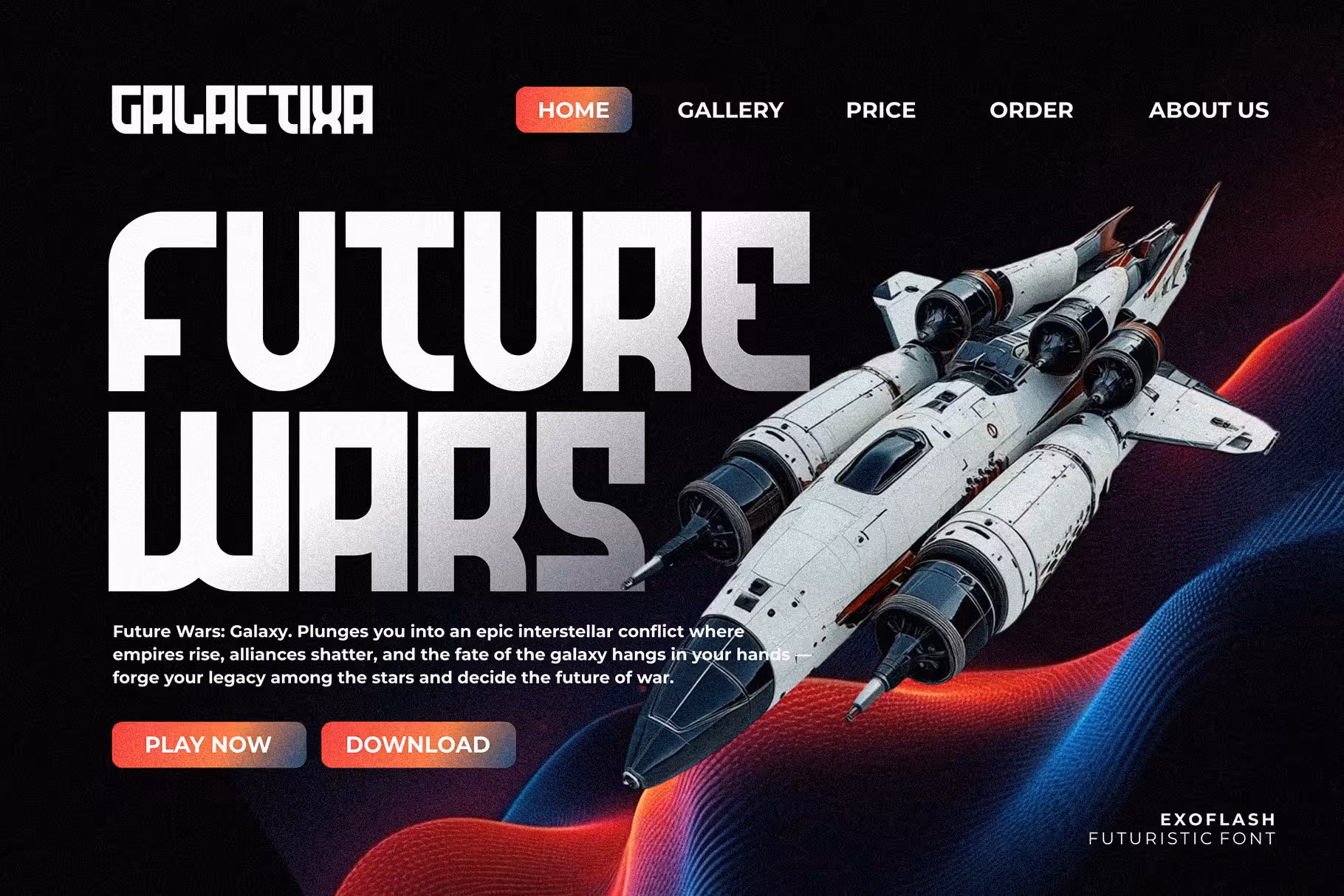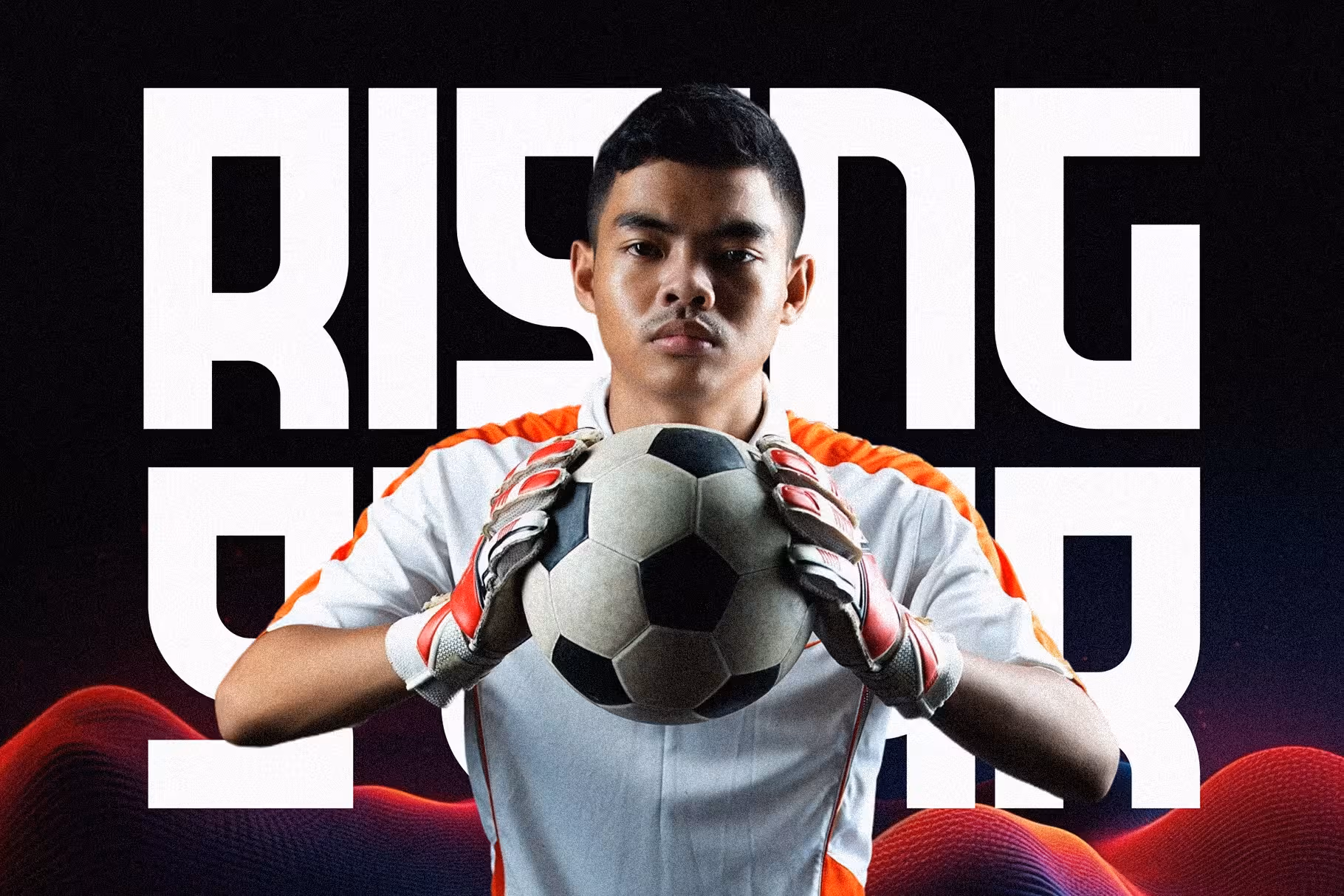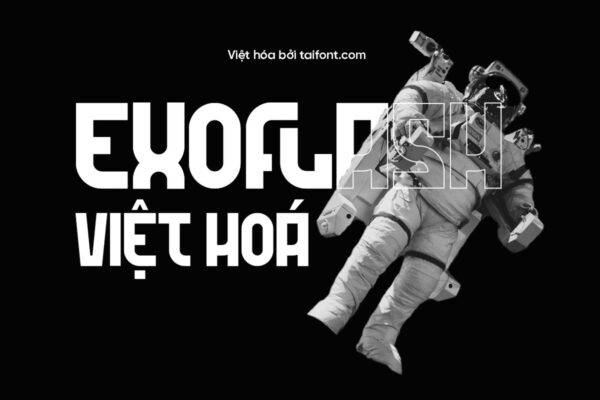
Giới thiệu về Font TF Exoflash Việt hóa
TF Exoflash Việt hóa là một font chữ không chân (sans-serif) nổi bật với thiết kế cao, sắc nét và đầy mạnh mẽ, mang đến vẻ ngoài hiện đại, năng động và có chút tương lai. Font này toát lên phong thái tốc độ, sự vươn lên và khám phá, lý tưởng để tạo điểm nhấn nổi bật và thu hút mọi ánh nhìn trong các thiết kế đòi hỏi sự táo bạo và phong cách đột phá.
Với đặc điểm là nét không chân cao, tính thẩm mỹ cao và phong thái ấn tượng, Exoflash là lựa chọn lý tưởng cho các thiết kế muốn truyền tải sự hiện đại, mạnh mẽ và sự độc đáo, đặc biệt là trong lĩnh vực:
- Thiết kế thể thao: Hoàn hảo cho logo, áo đấu, poster quảng cáo phòng gym, trung tâm thể hình, sự kiện thể thao, hoặc các thương hiệu liên quan đến thể thao. Font này giúp tạo không khí sôi động, cạnh tranh và mạnh mẽ, thúc đẩy tinh thần chiến thắng.
- Thiết kế liên quan tới vũ trụ: Lý tưởng để sử dụng trên poster phim khoa học viễn tưởng, tài liệu về không gian, các ấn phẩm quảng bá về công nghệ vũ trụ, hoặc các triển lãm thiên văn. Exoflash giúp tạo không khí khám phá, bí ẩn và đầy kỳ vĩ của vũ trụ.
- Thiết kế công nghệ cao: Phù hợp cho website, bao bì sản phẩm điện tử, hoặc các ấn phẩm truyền thông liên quan đến trí tuệ nhân tạo, robot, hoặc các công nghệ tiên tiến, giúp truyền tải sự tiên phong và hiện đại.
- Poster và Banner: Tạo các tiêu đề chính, slogan, hoặc thông điệp quảng cáo trên poster, banner cho các sự kiện, chương trình khuyến mãi, hoặc các sản phẩm muốn gây ấn tượng thị giác mạnh mẽ.
Với TF Exoflash Việt hóa, bạn có thể dễ dàng thổi hồn mạnh mẽ, năng lượng và sự độc đáo vào các thiết kế, tạo ra những sản phẩm không chỉ đẹp mắt mà còn cực kỳ ấn tượng và có khả năng thu hút sự chú ý tối đa.
Font Việt hóa TF Exoflash